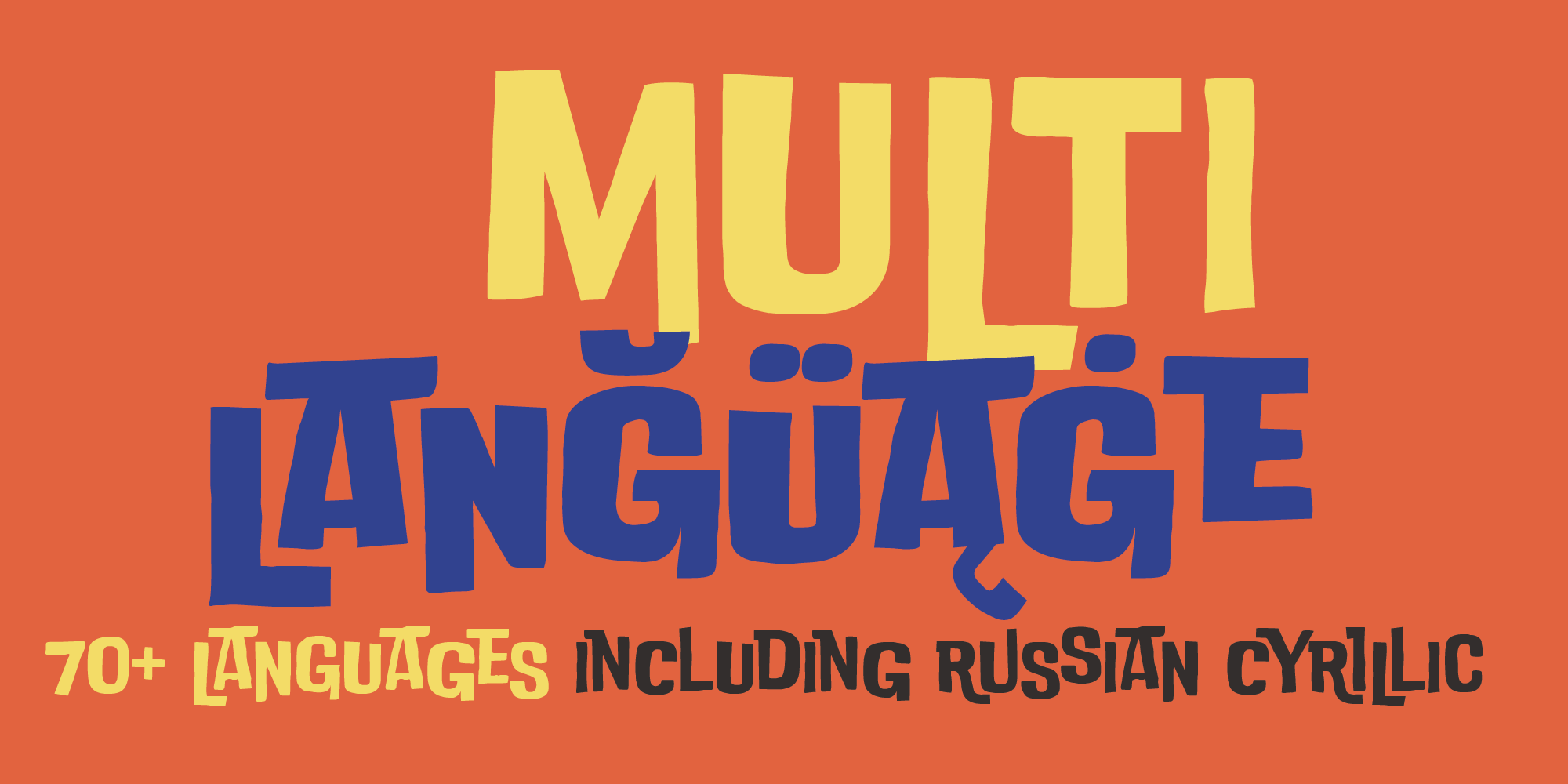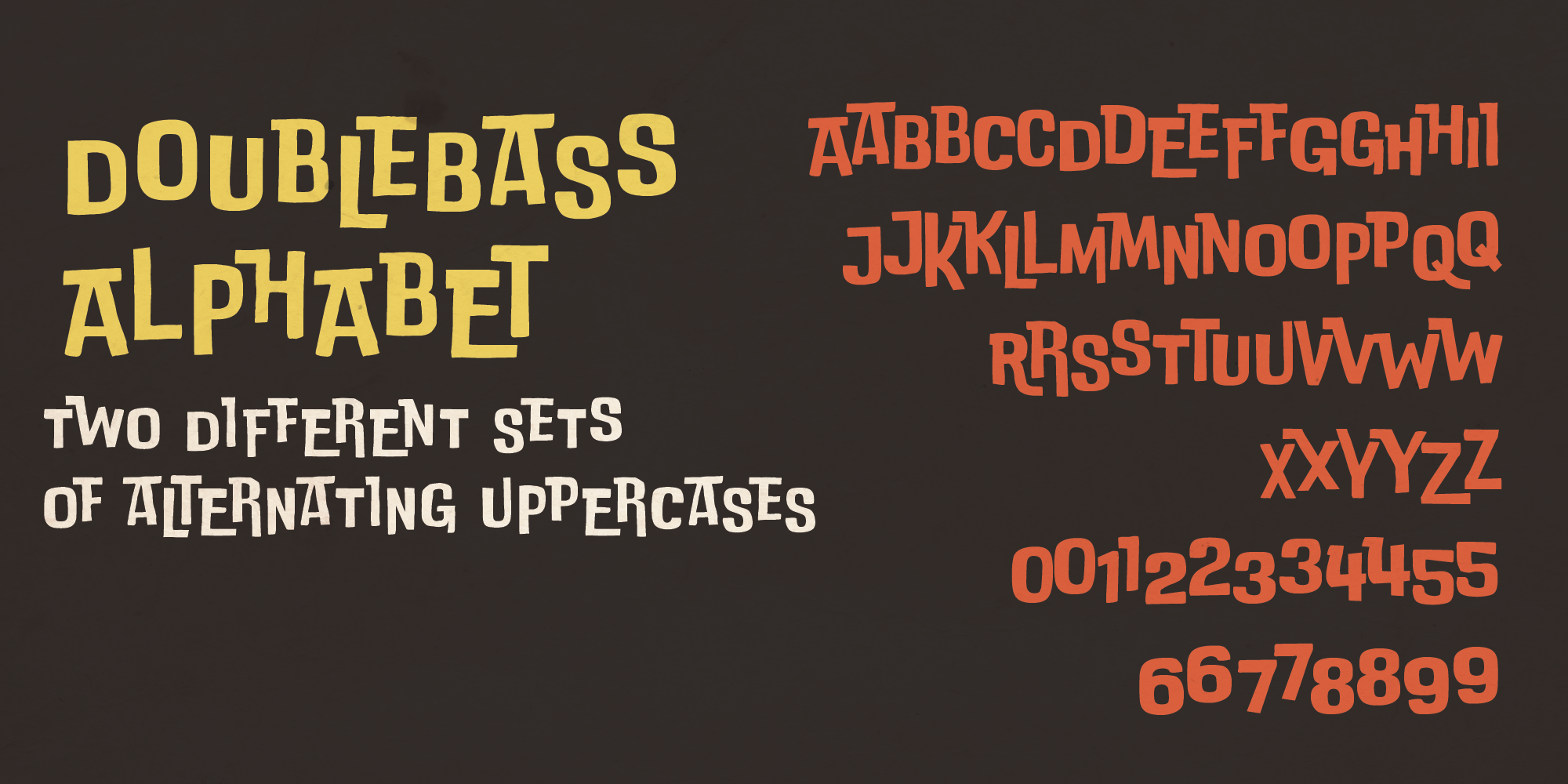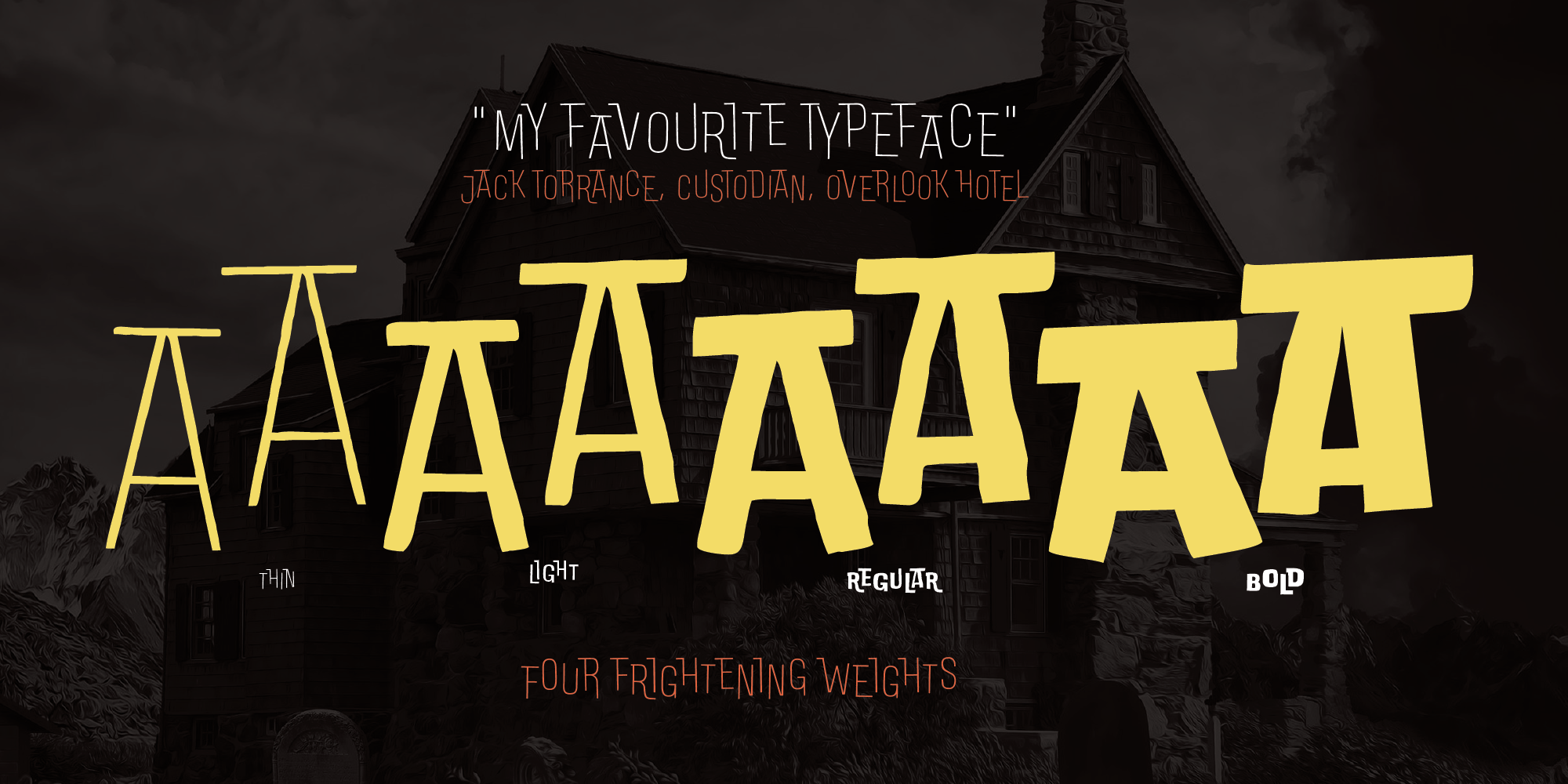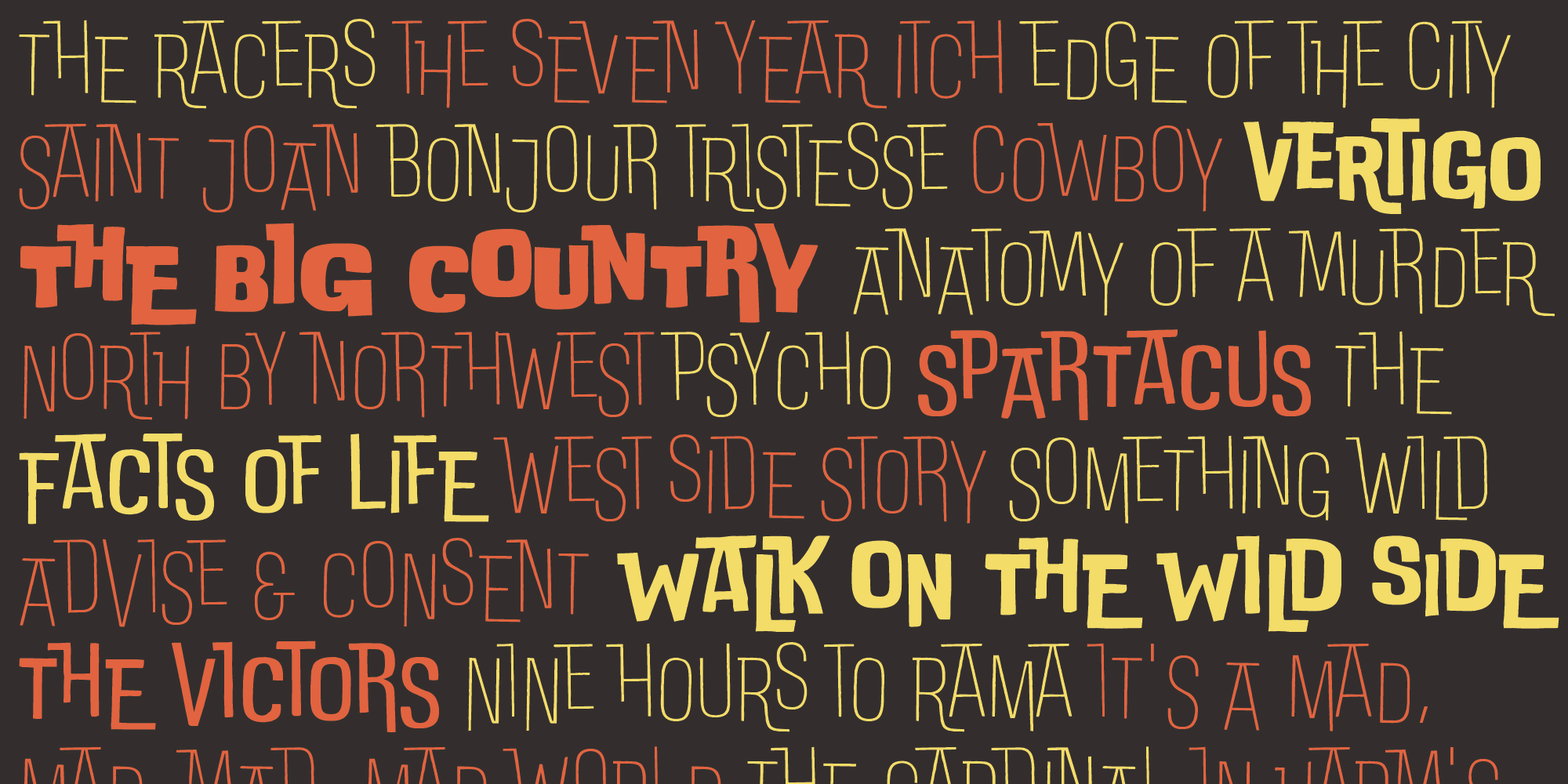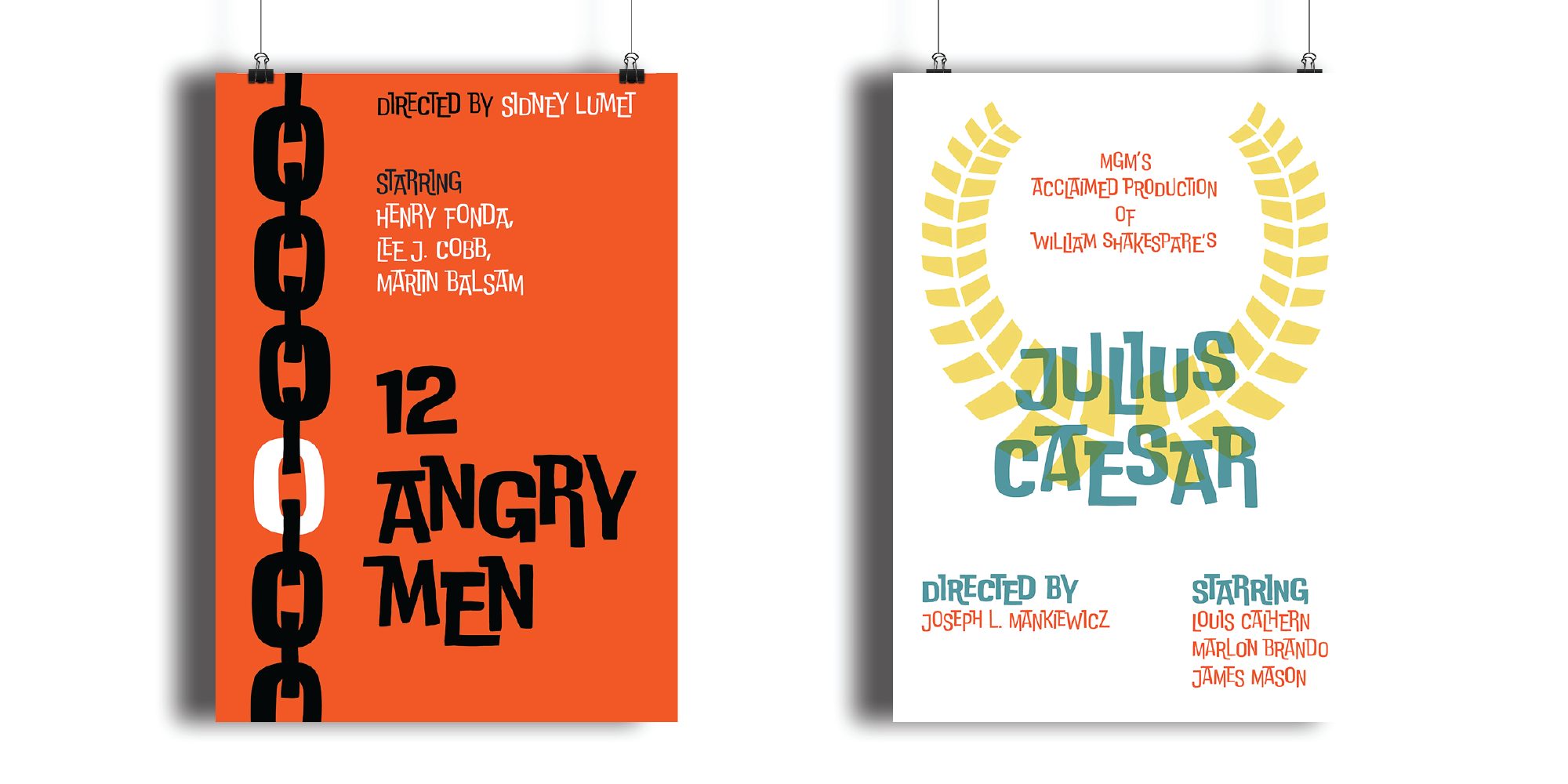
- Antiqua dekorativ
- Versaleszett:
- enthalten
Die Doublebass ist eine Versalschrift von Cosimo Lorenzo Pancini basiert auf dem Lettering-Stil von Saul Bass, insbesondere dessen Filmposter für »Der Mann mit dem goldenen Arm«. Der Stil wurde in eine Satzschrift in vier Strichstärken verwandelt. Enthalten ist eine erweiterte lateinische und eine kyrillische Belegung. Die vielen Alternativzeichen unterstützen dabei den Eindruck einer Lettering-Arbeit, da die Strichenden über vorhergehende und nachfolgende Buchstaben ragen. Dies wird jedoch nicht durch Ligaturen erreicht, sondern allein durch die Abfolge der Alternativzeichen.